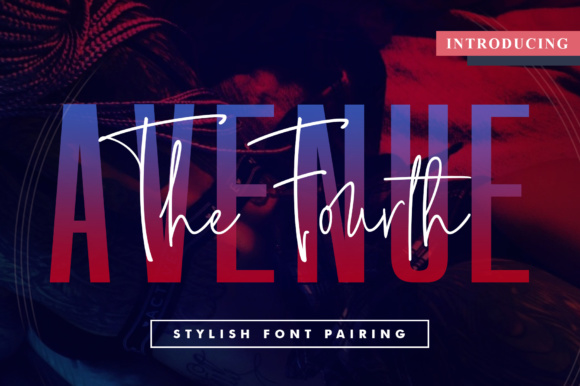
The Fourth Avenue 3 Font – لمسة إبداعية لعشاق التصميم
اكتشف The Fourth Avenue 3 Font، حزمة خطوط أنيقة ومبتكرة تضيف طابعًا عصريًا وفريدًا إلى مشاريعك الإبداعية. يتميز هذا الخط بتصميمه الأنيق والمتعدد الاستخدامات، مما يجعله مثاليًا لمجموعة متنوعة من التطبيقات، بما في ذلك:
✔️ الشعارات والهوية البصرية
✔️ تصاميم العلامات التجارية
✔️ الدعوات والبطاقات
✔️ منشورات وسائل التواصل الاجتماعي
✔️ أغلفة الكتب والمجلات
لماذا تختار The Fourth Avenue 3 Font؟
✅ تصميم احترافي ومتناسق